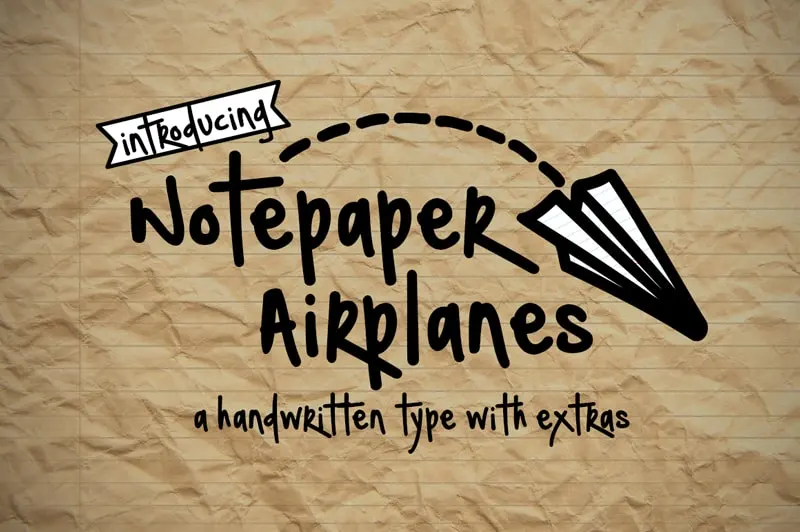
Notepaper Airplanes font – Fonte Grátis
Notepaper Airplanes font
Esta fonte chamada Notepaper Airplanes é perfeita para quem gosta de uma pitada de personalidade nos seus documentos escritos a mão. Seja você um escritor apaixonado por passar mensagens pessoais aos amigos, ou um blogueiro que deseja dar um toque único às suas postagens, essa fonte não pode faltar em seu arsenal. Ela traz um toque descontraído e elegante ao texto com uma escrita a mão cuidadosamente feita, ideia perfeita para aqueles momentos de intimidade através dos papéis de notas. Mas o charme da Notepaper Airplanes vai além. Como se não bastasse sua facilidade em expressar sentimentos pessoais, ela traz um conjunto adicional de funções que elevam ainda mais a experiência ao usar essa fonte. Com extras como flechas, ícones, bandejas e mais, você pode personalizar seus documentos para refletir a natureza rica e diversificada do seu estilo. Admiramos o trabalho de Hamilton na criação dessa notável fonte. Que venham muitas novas maneiras criativas para usar suas ferramentas únicas. Com a Notepaper Airplanes, qualquer documento pode ser uma viagem em direção à sua personalidade única e ao coração da sua mensagem.